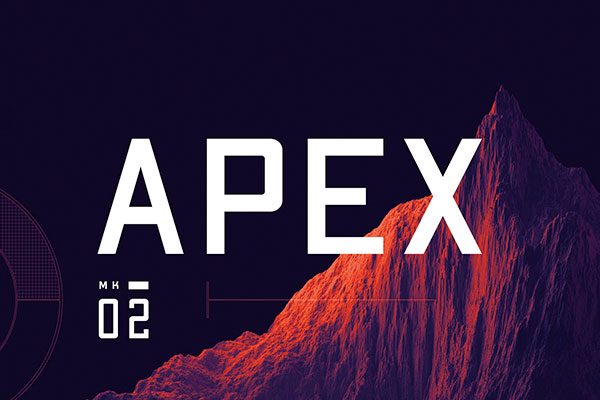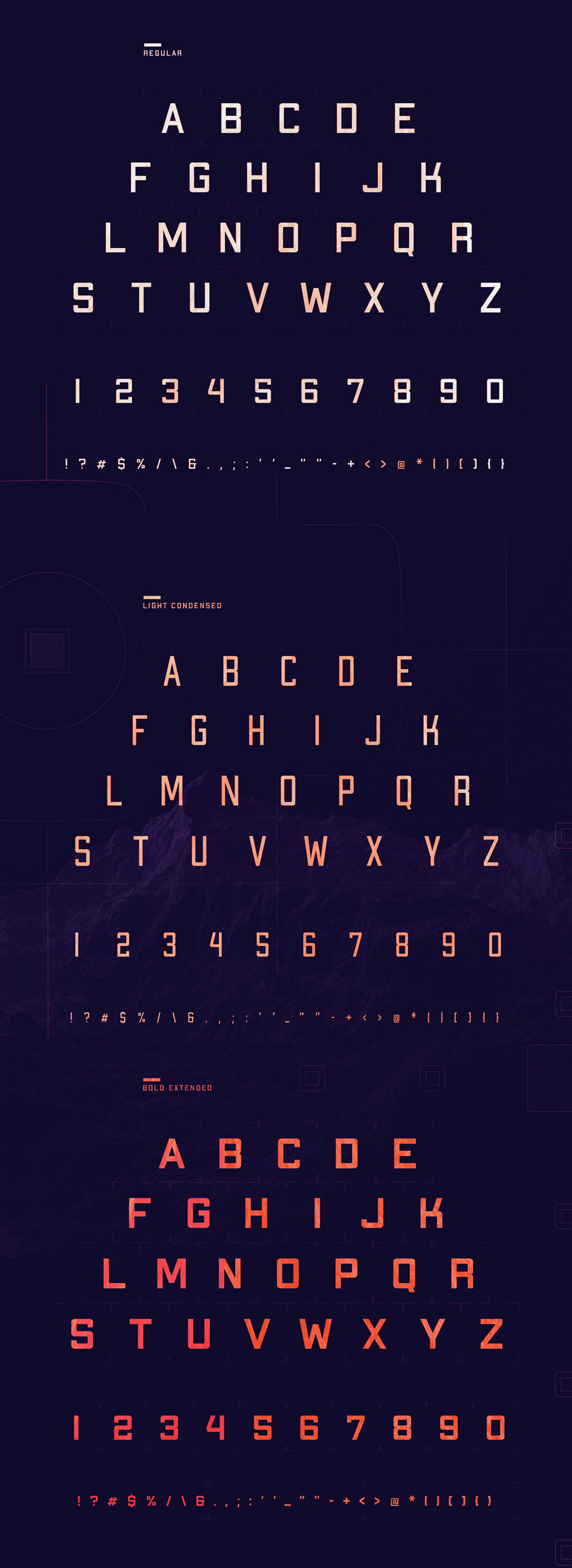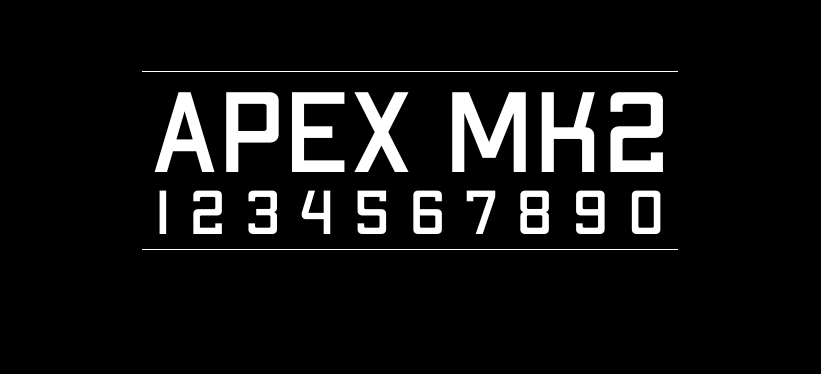
Apex Mk2
Apex Mk2字体介绍
APEX Mk2的作者美国的Jeremy Nelson,是一款英文字体,其灵感来自经典无衬线和运动字体设计的多功能主力几何块字体。
看到APEX Mk2大家应该有些似曾相识,因为自由字体之前已经发布过该作者的另外一款字体APEX Mk3,这两款字体字形风格相似,细节上有一些区别。
Apex Mk2字体应用示例